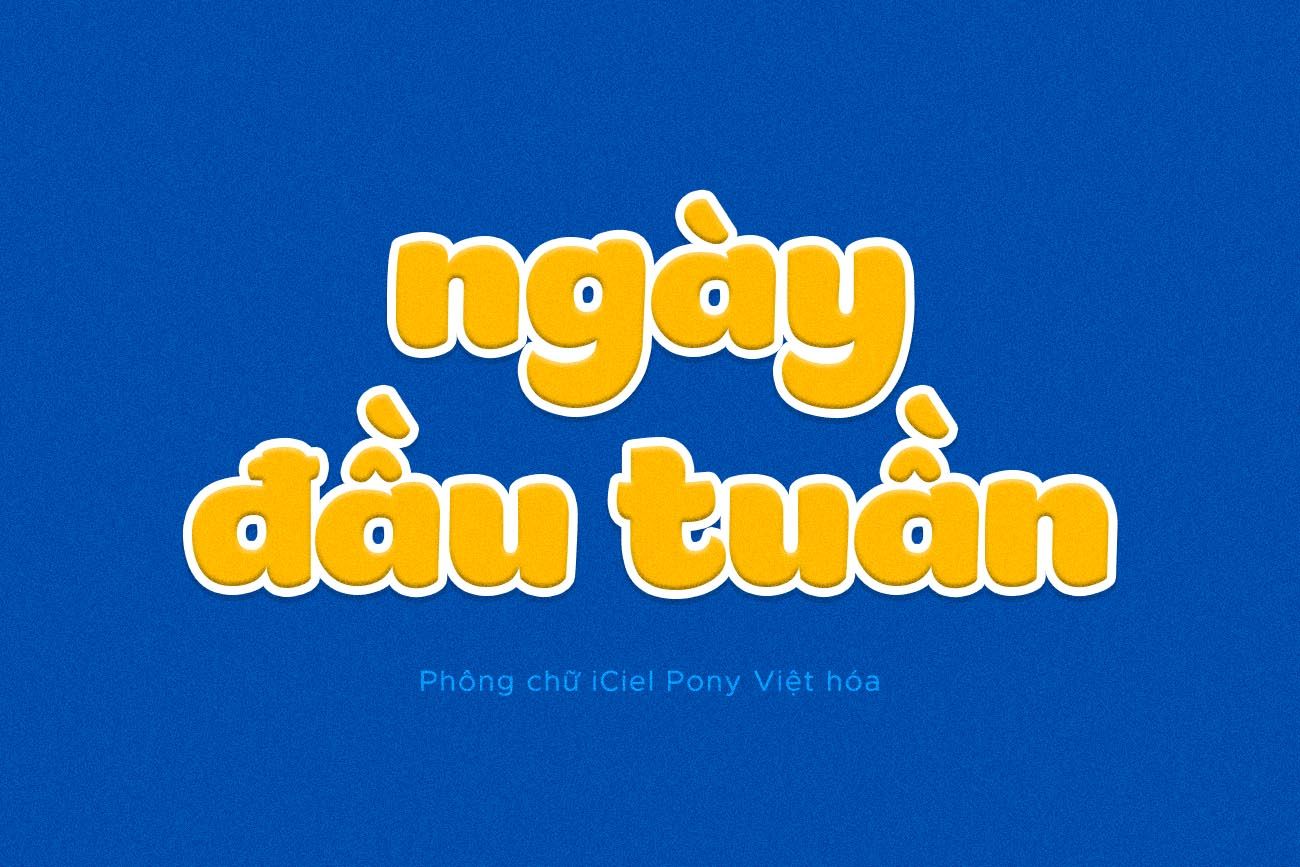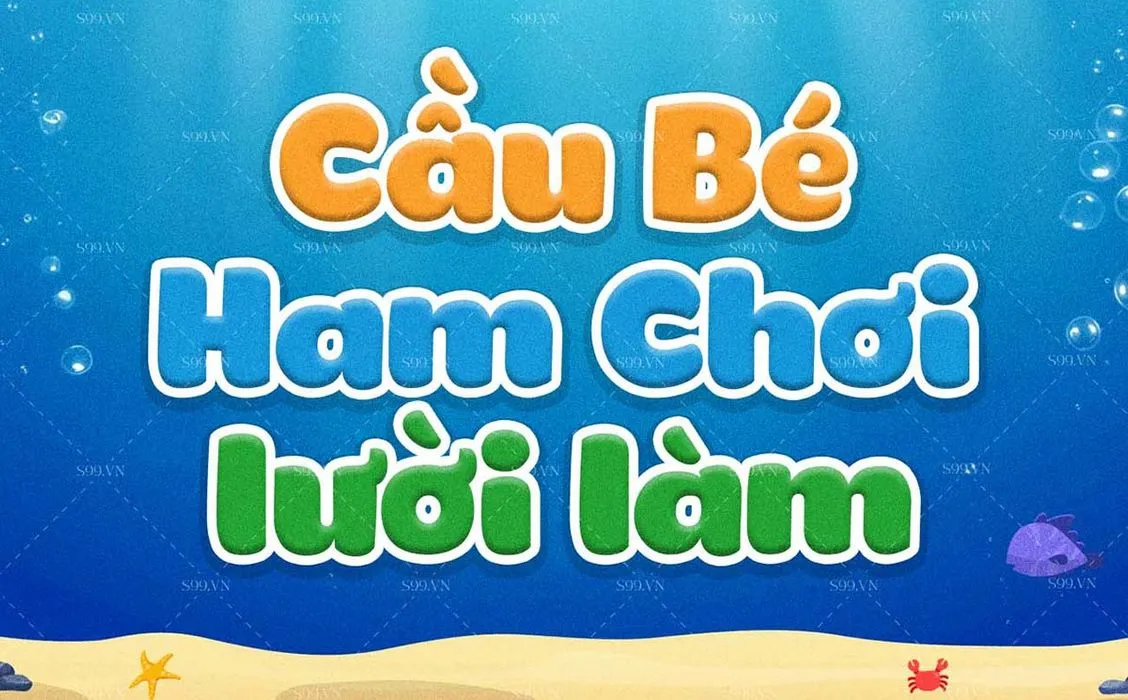
Tác giả Rodrigo Araya Sala
Thông tin font chữ iCiel Pony
Font iCiel Pony là một lựa chọn lý tưởng dành cho những ai đang tìm kiếm một kiểu chữ vừa đáng yêu vừa độc đáo. Thuộc nhóm font chữ béo tròn, bộ chữ này mang đến cảm giác mũm mĩm, vui nhộn nhưng vẫn giữ được sự tinh tế trong từng đường nét. Được sáng tạo bởi Rodrigo Araya Sala và Việt hóa bởi iCiel Team, font chữ iCiel Pony hỗ trợ đầy đủ dấu tiếng Việt, giúp người dùng dễ dàng ứng dụng trong nhiều dự án thiết kế.
Điểm nổi bật của iCiel Pony font nằm ở dáng chữ bo tròn mềm mại, gợi liên tưởng đến phong cách font chữ hoạt hình và mang đậm tính trẻ trung. Chính vì thế, nó được nhiều designer lựa chọn để sử dụng trong poster sự kiện, bìa sách thiếu nhi, thiệp mời sinh nhật, hoặc các dự án cần tạo cảm giác vui vẻ, gần gũi. Với những đường nét font chữ mũm mĩm, iCiel Pony không chỉ đáng yêu mà còn giúp thiết kế trở nên dễ nhận diện và ghi dấu ấn mạnh mẽ trong mắt người xem.
Bên cạnh đó, sự đáng yêu và ngộ nghĩnh khiến iCiel Pony trở thành một trong những font chữ cute được yêu thích nhất trong cộng đồng thiết kế. Nó mang lại cảm giác tự nhiên, thân thiện và cực kỳ phù hợp cho các sản phẩm hướng đến trẻ em hoặc những thiết kế cần khơi gợi sự hứng thú. Đây cũng là một trong những font chữ Việt hóa hiếm hoi vừa giữ được tinh thần của bản gốc, vừa đáp ứng đầy đủ nhu cầu sáng tạo bằng tiếng Việt.
Tóm lại, font chữ đáng yêu iCiel Pony chính là lựa chọn hoàn hảo để bạn mang lại sự khác biệt cho thiết kế, từ logo, banner quảng cáo, đến các ấn phẩm nghệ thuật mang tính giải trí và sáng tạo.